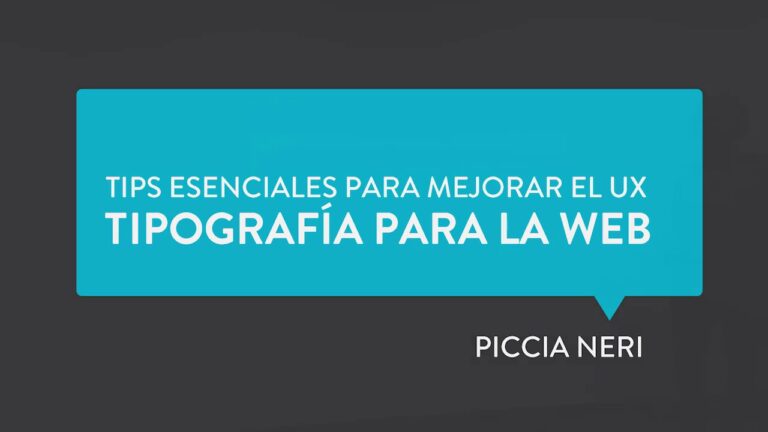
Tipografía Legible: Mejora la Experiencia de Usuario
La tipografía legible es un elemento fundamental para mejorar la experiencia de usuario en cualquier plataforma digital. Un buen diseño tipográfico no solo facilita la lectura, sino que también guía al usuario a través del contenido de manera fluida y agradable. Al elegir fuentes claras y adecuadas, se potencia la comprensión y se reduce la fatiga visual, lo que resulta en una interacción más rendidora y satisfactoria. En este artículo, estudiaremos cómo la tipografía puede transformar la experiencia del usuario y ofreceremos consejos prácticos para implementarla de manera rendidora en tus proyectos.
¿Cómo elegir tipografía legible para usuarios?
Para elegir una tipografía legible, opta por fuentes sans-serif, tamaño adecuado, alto contraste y suficiente espacio entre líneas. Esto mejora la experiencia de usuario.
¿Cuál es la fuente más fácil de leer?
La legibilidad de una tipografía es vital en el diseño gráfico y la comunicación visual. Entre las opciones más destacadas se encuentra Helvetica, una fuente sans serif reconocida por su claridad y simplicidad. Su estructura geométrica y sus líneas limpias permiten que el texto se lea con facilidad, lo que la convierte en una elección popular en una variedad de contextos, desde señalización hasta diseño web.
Otra fuente que también se distingue por su legibilidad es Georgia. A diferencia de Helvetica, Georgia es una tipografía serif que se diseñó específicamente para ser legible en pantallas. Su estilo clásico, con un alto contraste y un espacio generoso entre caracteres, facilita la lectura en dispositivos digitales, lo que ha llevado a su adopción en numerosos sitios web y publicaciones en línea.
Ambas tipografías, Helvetica y Georgia, demuestran que la legibilidad no solo se trata de la estética, sino también de la funcionalidad. La elección de una tipografía adecuada puede mejorar ostensiblemente la experiencia del lector, habilitando que el mensaje se comunique de manera rendidora y atractiva. Así, tanto diseñadores como editores deben considerar cuidadosamente estas opciones para lograr una comunicación visual óptima.
¿Cuál es la tipografía que transmite confianza?
Las tipografías slab serif se caracterizan por sus líneas robustas y sus serifas menos delicadas, lo que les otorga una imagen poderosa y audaz. Esta estética visual no solo capta la atención, sino que también genera una sensación de confianza y fiabilidad en quienes las observan. Al ser menos ornamentadas que otras tipografías, las slab serif proyectan una claridad que resulta atractiva en diversas aplicaciones, desde logotipos hasta publicaciones impresas.
Además de su impacto visual, estas fuentes están asociadas al pensamiento creativo, lo que las convierte en una opción ideal para marcas que buscan destacar su innovación y solidez. Al elegir una tipografía slab serif, se establece una conexión inmediata con el público, transmitiendo un mensaje de seguridad y profesionalismo que puede ser decisivo en la percepción de una marca o proyecto.
¿Cuál es la tipografía más adecuada para aumentar la legibilidad en un material educativo?
Para mejorar la legibilidad en materiales educativos, es fundamental elegir la tipografía adecuada. Las fuentes sans-serif, como Arial o Helvetica, son perfectas para el cuerpo del texto debido a su claridad y simplicidad, lo que facilita la lectura. Por otro lado, las fuentes serif, como Times New Roman o Georgia, son ideales para títulos y subtítulos, ya que aportan un toque de elegancia y ayudan a diferenciar secciones. Al combinar estas tipografías de manera rendidora, se logrará un diseño atractivo y fácil de seguir, favoreciendo así la comprensión del contenido.
Optimiza la Lectura con Estilos Atractivos
La lectura es una puerta abierta al conocimiento y la imaginación, y optimizarla puede transformar la experiencia del lector. Al elegir estilos atractivos, como tipografías legibles y colores que estimulen la vista, se puede mejorar la concentración y el disfrute del texto. Un diseño visualmente agradable no solo atrae la atención, sino que también facilita la comprensión de la información presentada.
Además, la organización del contenido juega un papel vital en la optimización de la lectura. Utilizar encabezados claros, listas y espacios adecuados permite al lector navegar por el material de manera más rendidora. Esto no solo ayuda a retener la información, sino que también reduce la fatiga visual, creando un ambiente más propicio para el aprendizaje y la reflexión. La claridad y la estructura son aliados indispensables en la búsqueda de una lectura más placentera.
Finalmente, la interacción con el contenido puede ser enriquecida mediante elementos multimedia. Incluir imágenes, videos o infografías complementa el texto y lo hace más dinámico. Estas herramientas visuales no solo capturan el interés del lector, sino que también refuerzan los conceptos clave, facilitando una mejor asimilación del contenido. Al integrar estilos atractivos con un enfoque interactivo, se logra una experiencia de lectura más completa y satisfactoria.